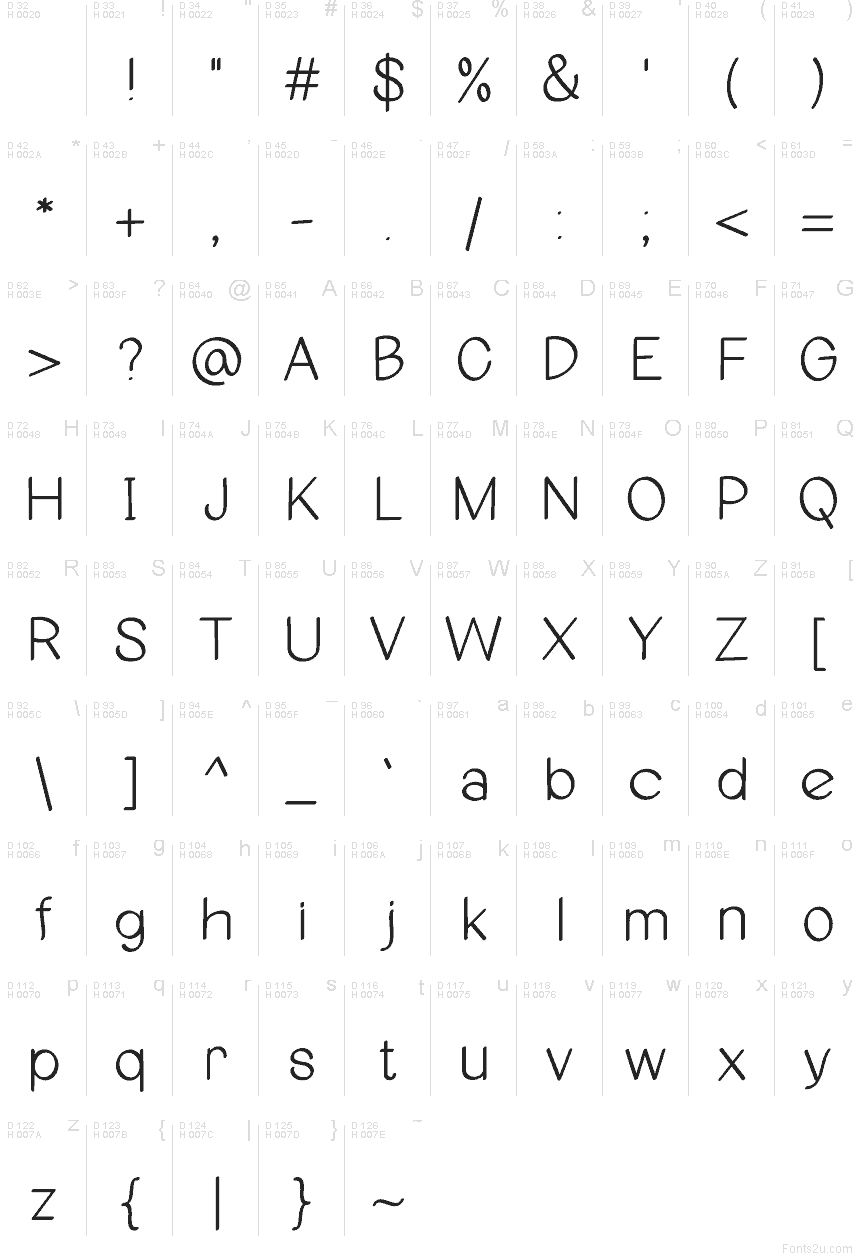
Sanstosons هو خط يدوي مجاني يتميز بضربات ناعمة ومستديرة، وإيقاع عالٍ ومفتوح يضفي على الحروف انسيابية طبيعية ومريحة. تظل أشكال الحروف بسيطة وجذابة، مع منحنيات ناعمة وطابع مرسوم باليد يعمل بشكل رائع مع الكلمات القصيرة والأسماء الطويلة على حد سواء.
يناسب خط Sanstosons تصميم الدعوات، الشعارات (اللوغو)، التصاميم التي تحتوي على اقتباسات، التغليف، ومنشورات وسائل التواصل الاجتماعي التي تتطلب لمسة يدوية دون الحاجة إلى زخرفة إضافية. يسهل هذا الخط المجاني هذه الاستخدامات بفضل وضوح وتوازن أشكال الحروف، مع الحفاظ على طابع شخصي وغير رسمي.